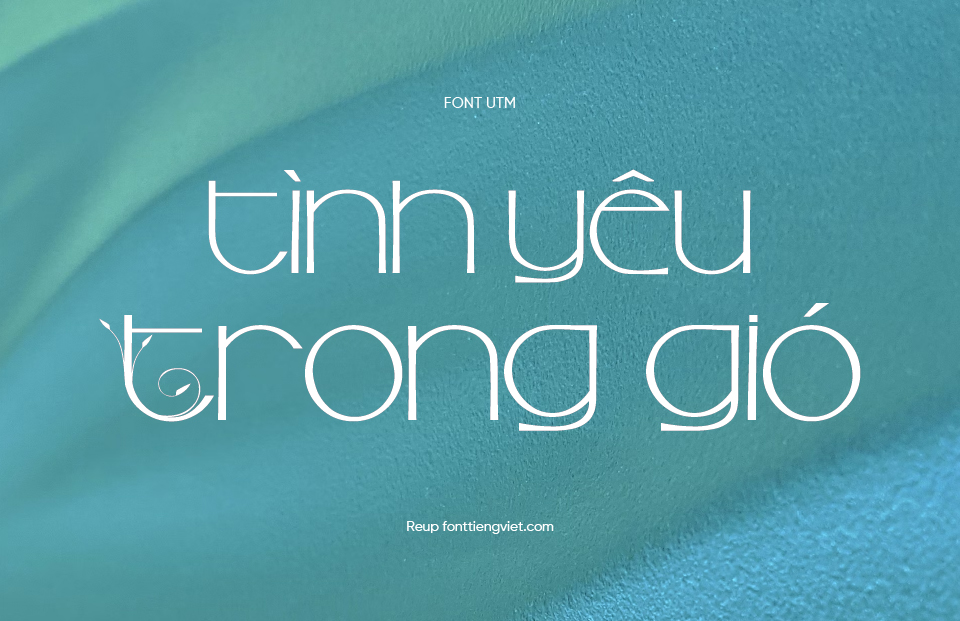
Font Việt hóa UTM Camellia ( 2 font )
Giới thiệu bộ Font Việt hóa UTM Camellia ( 2 font ) chuyên nghiệp
Trong cộng đồng thiết kế đồ họa tại Việt Nam, Font Miễn Phí luôn là nguồn tài nguyên quý giá giúp các bạn học sinh và giáo viên sáng tạo bài giảng sinh động. Trong đó, bộ Font Việt hóa UTM Camellia ( 2 font ) nổi bật như một lựa chọn hoàn hảo cho những dự án đòi hỏi sự tinh tế và thanh lịch. Với cấu trúc đường nét mềm mại, bộ phông chữ này không chỉ giúp nội dung trở nên dễ đọc mà còn mang lại cảm giác nghệ thuật đương đại, phù hợp cho cả in ấn lẫn trình chiếu kỹ thuật số.
Đặc điểm nổi bật của Font Việt hóa UTM Camellia
Bộ Font Việt hóa UTM Camellia ( 2 font ) bao gồm hai định dạng kiểu chữ khác nhau, cho phép người dùng linh hoạt thay đổi giữa phong cách mảnh mai hoặc đậm nét tùy theo mục đích sử dụng. Điểm đặc biệt của bộ font này chính là khả năng hiển thị tiếng Việt hoàn hảo, không bị lỗi dấu, giúp các bạn yên tâm khi soạn thảo văn bản. Nhờ vào thiết kế tối giản nhưng không kém phần sang trọng, UTM Camellia thường được ứng dụng rộng rãi trong việc làm thiệp mời, bìa sách hoặc các tiêu đề trang trí trong môi trường học đường.
Cách ứng dụng Font Việt hóa UTM Camellia ( 2 font ) hiệu quả
Để tận dụng tối đa vẻ đẹp của Font Việt hóa UTM Camellia ( 2 font ), bạn nên kết hợp chúng với các tông màu pastel hoặc màu trung tính. Việc sử dụng biến thể Regular cho phần nội dung và biến thể Bold cho tiêu đề sẽ tạo nên một bố cục phân cấp rõ ràng, thu hút ánh nhìn của người xem ngay từ lần đầu tiên. Đây là công cụ đắc lực để biến các slide thuyết trình khô khan trở nên lôi cuốn và chuyên nghiệp hơn bao giờ hết.
Tổng kết về bộ font chữ UTM Camellia